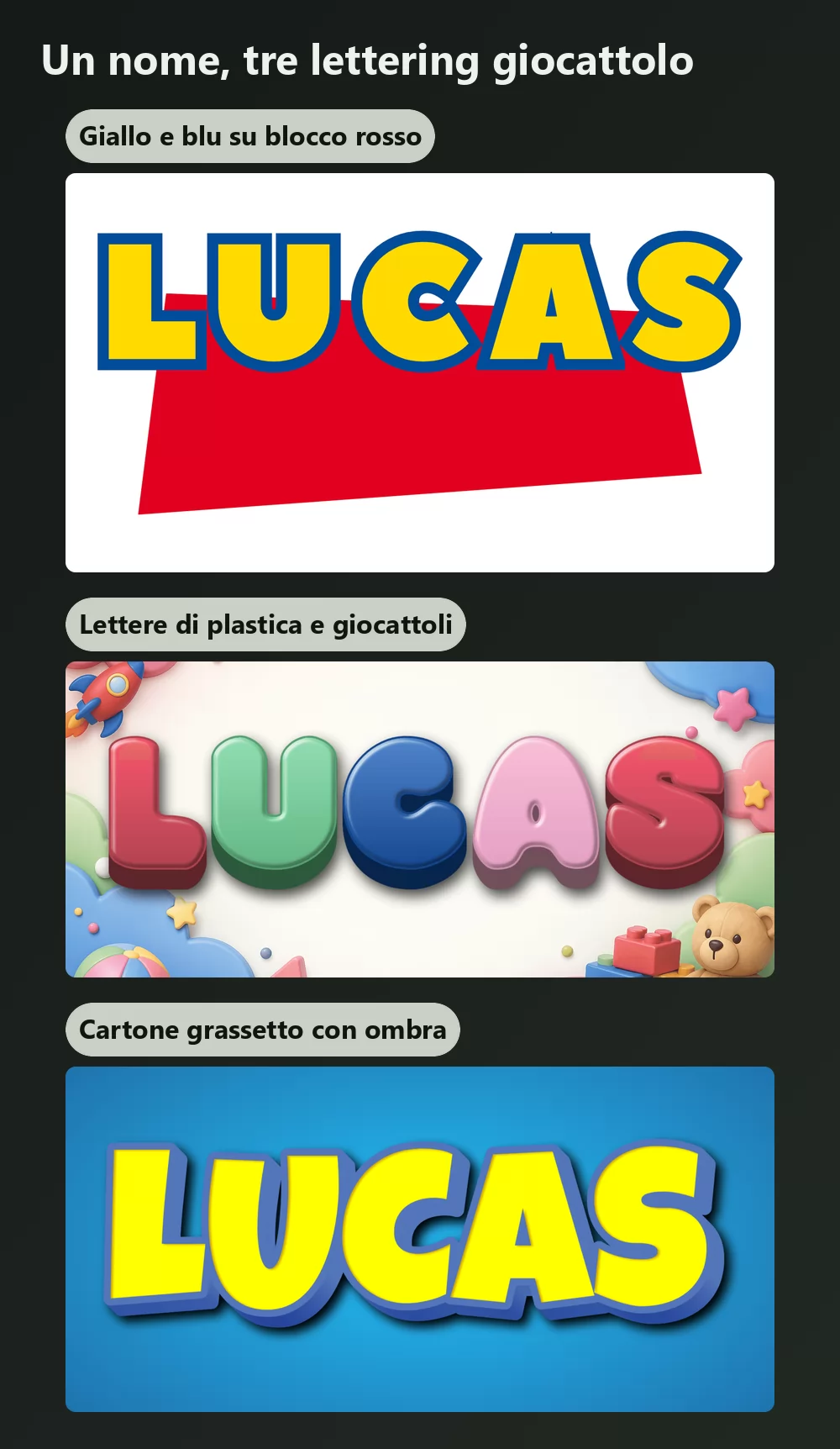
Cerca il font di Toy Story e troverai un lungo elenco di download che sembrano tutti leggermente sbagliati. Non è sfortuna. Il logo di Toy Story non è un carattere, sono due, e la maggior parte delle pagine di download ti dà solo un'approssimazione di uno dei due.
Questa guida separa i due, dice esattamente cosa puoi fare con ciascuno (è qui che quasi tutte le pagine restano vaghe), elenca i quattro ingredienti che fanno davvero leggere «Toy Story» e mostra come arrivarci senza installare nulla. Tutte le immagini qui sotto vengono dal generatore di font Toy Story di TextStudio.
Il logo sono due caratteri, non uno
La parola «TOY» è il lettering grosso e arrotondato che tutti hanno in mente. È stato disegnato per il film. Non è mai stato pubblicato come carattere, quindi non esiste alcun file legittimo da nessuna parte.
La parola «STORY» è la parola piccola dentro la forma rossa, ed è un carattere commerciale vero: Gill Sans Ultra Bold. Eric Gill disegnò la famiglia Gill Sans per Monotype nel 1928; il peso Ultra Bold è il più grasso, quello usato qui.
Questa divisione spiega la delusione dei download. Un file chiamato «font Toy Story» ti dà un sosia della metà disegnata a mano e niente per l'altra, mentre è l'unione delle due a far funzionare la composizione.
La metà «TOY» non è mai stata pubblicata, quindi quali sosia?
I nomi che tornano di continuo sono Agent Red e Agent Orange di Pizzadude, oltre a SF Slapstick Comic. Sono vicini nello spirito: maiuscole grasse, tonde e un po' traballanti.
Il confine pratico: personalizza liberamente per te e per i tuoi, e fermati prima di qualsiasi cosa che vendi o che serve a promuovere un'attività.
Cosa fa davvero leggere «Toy Story»
È la parte che le pagine di download saltano, e pesa più del font esatto. Quattro elementi fanno il lavoro:
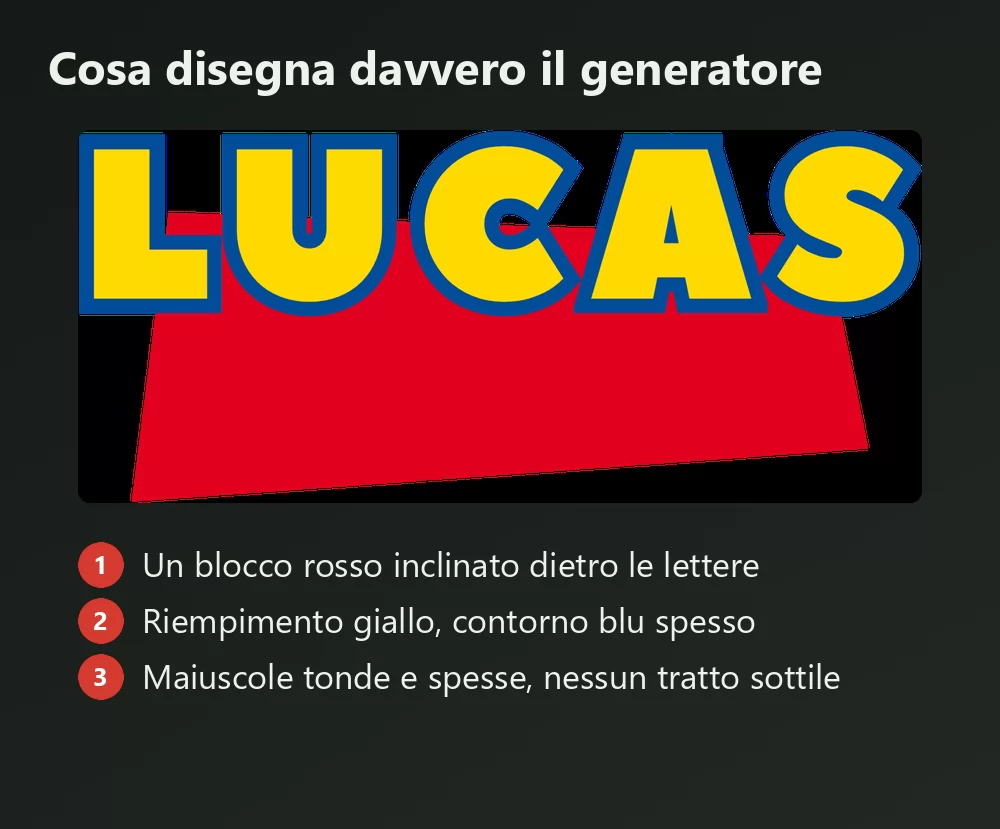
- Un quadrilatero rosso inclinato da un lato, posto dietro il titolo come una macchia di colore e non come un rettangolo ordinato.
- Il titolo inclinato dal lato opposto, così che i due angoli si contrappongano. Questa contro-inclinazione porta quasi tutta l'energia della composizione.
- Riempimento giallo con un contorno blu pesante, la coppia di colori primari su cui gira tutta la saga.
- Lettere leggermente storte, ognuna al suo piccolo angolo, come sistemate da un bambino invece che composte.
Azzecca questi quattro punti e lo stile regge anche con un carattere approssimativo. Azzecca il carattere esatto ma salta la contro-inclinazione, e non ricorderà Toy Story per niente.
Una nota onesta sull'immagine qui sopra: il generatore ti dà il blocco rosso inclinato, il riempimento giallo e il contorno blu, e posa il testo dritto. Se vuoi la contro-inclinazione e gli angoli lettera per lettera dell'originale, esporta il PNG trasparente e ruotalo tu di qualche grado. Quest'ultimo passaggio richiede cinque secondi ed è la differenza tra «vicino» e «giusto».
Ho già Gill Sans? Su Mac sì. Con Microsoft Office installato sì. Su Windows senza Office no.
Che colori usa il logo di Toy Story? Lettere gialle con contorno blu, su un blocco rosso. Primari accesi ovunque, il che spiega in buona parte perché lo stile si riconosce a colpo d'occhio.